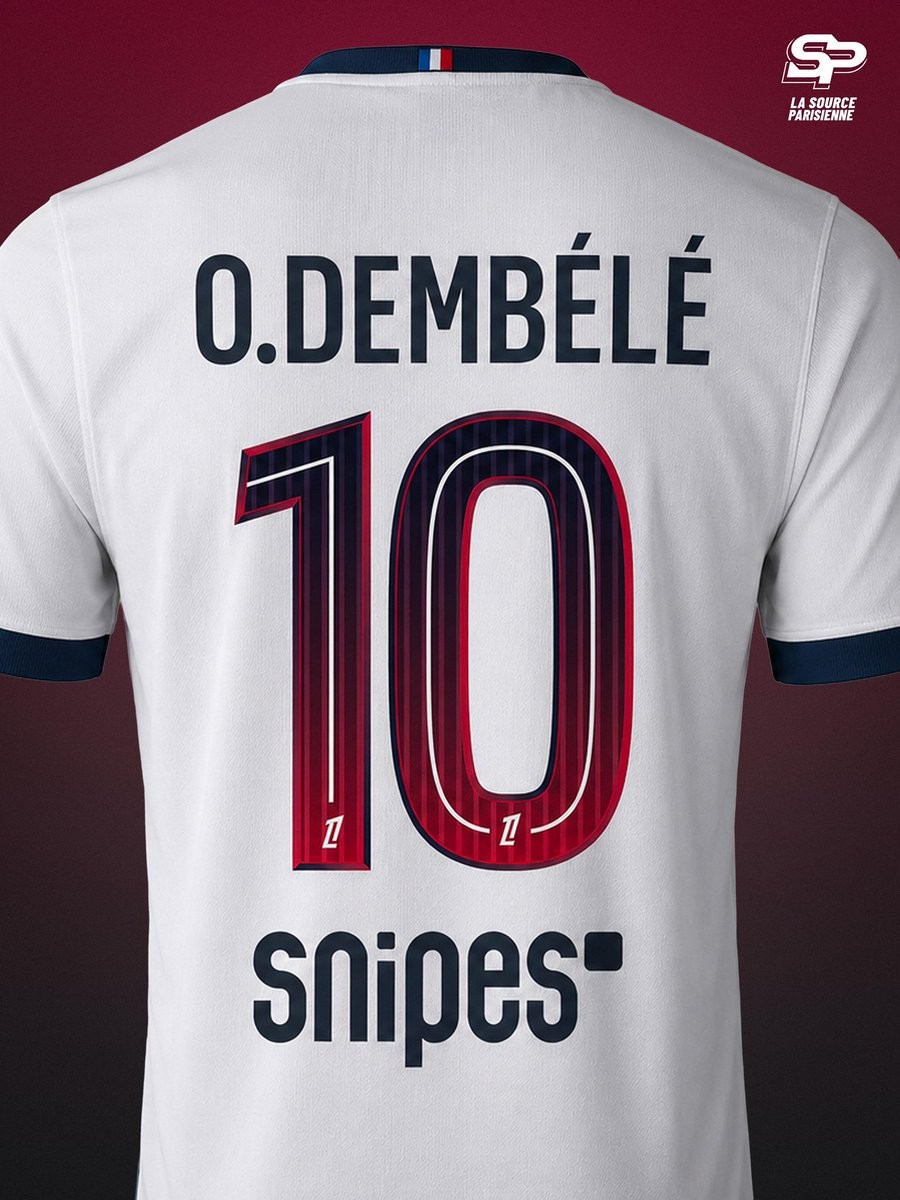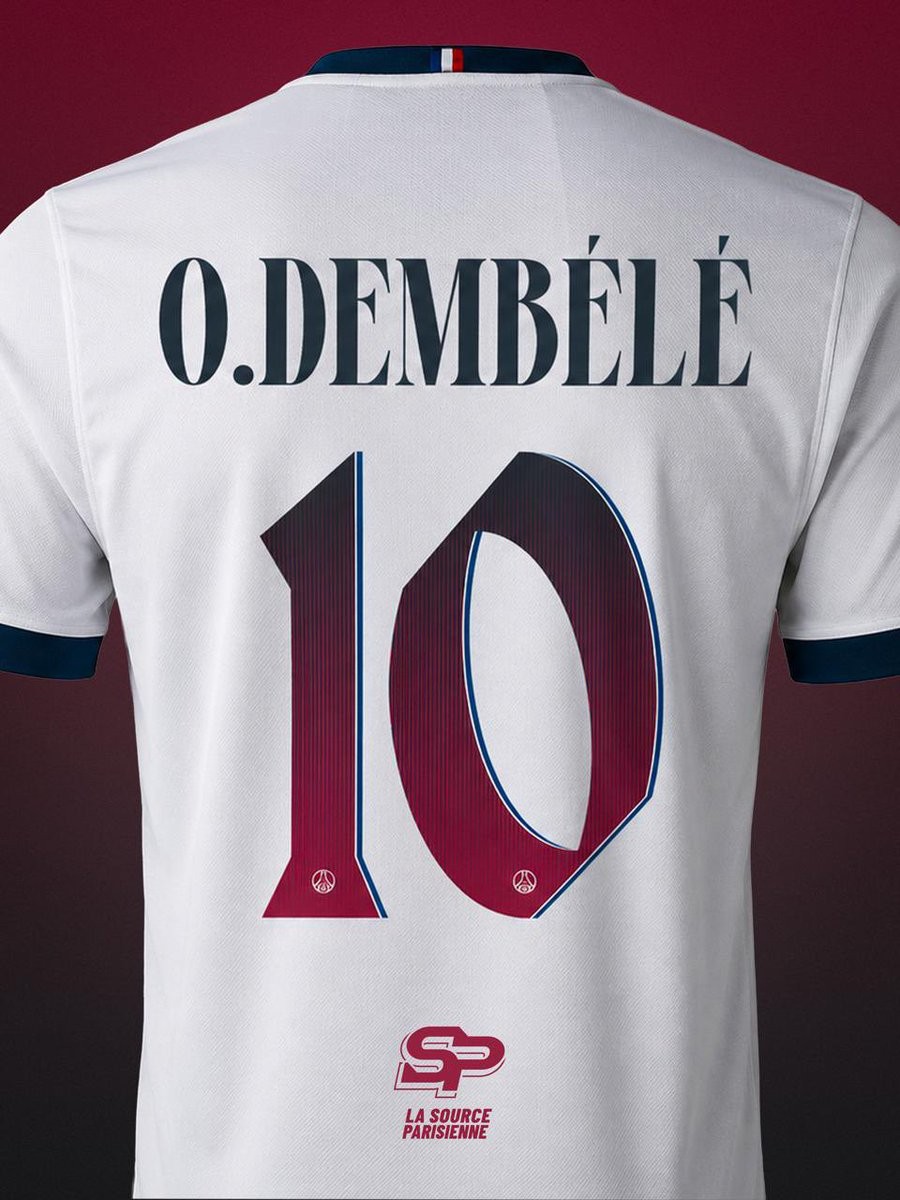
PSG 26-27 Auswärtstrikot-Schriftarten veröffentlicht
• Offizielle Veröffentlichung: Die offiziellen Schriftarten für das Auswärtstrikot von Paris Saint-Germain für die Saison 2026/27 wurden nach der offiziellen Vorstellung und Insider-Informationen bestätigt.
• Zwei Schriftvarianten: Auf dem kommenden Auswärtstrikot kommen zwei unterschiedliche Schriftvarianten zum Einsatz, eine für die Champions League und eine für die Ligue 1.
• Designmerkmale der Schriftarten: Die Champions-League-Schrift zeichnet sich durch stilisierte, vom Art-Déco-Stil inspirierte Namen und Nummern aus, während die Ligue-1-Schrift ein schlichtes Design mit einem Farbverlauf aufweist.
Die offizielle Schriftart für das Auswärtstrikot von Paris Saint-Germain für die Saison 2026/27 wurde nach der offiziellen Vorstellung und Infos von PSG-Insidern bei La Source Parisienne bestätigt. Leider gibt PSG keinen vollständigen Überblick über die Schriftarten.
PSG 26-27 Auswärtstrikot-Schriftarten veröffentlicht
Schriftart des PSG-Auswärtstrikots 26–27
Champions League & Ligue 1.
Auf dem kommenden Auswärtstrikot kommen zwei Varianten der Schrift zum Einsatz. Die Champions-League-Version zeichnet sich durch stilisierte, vom Art-Déco-Stil inspirierte Namensschriften und Spielernummern aus, während das Schriftdesign für die Ligue 1 auf der schlichten Schriftart basiert, aber zusätzlich eine Eigenschaft mit Farbverlauf enthält.
Champions League PSG 26-27 Champions-League-Auswärtstrikot
PSG Auswärtstrikot Ligue 1 26–27